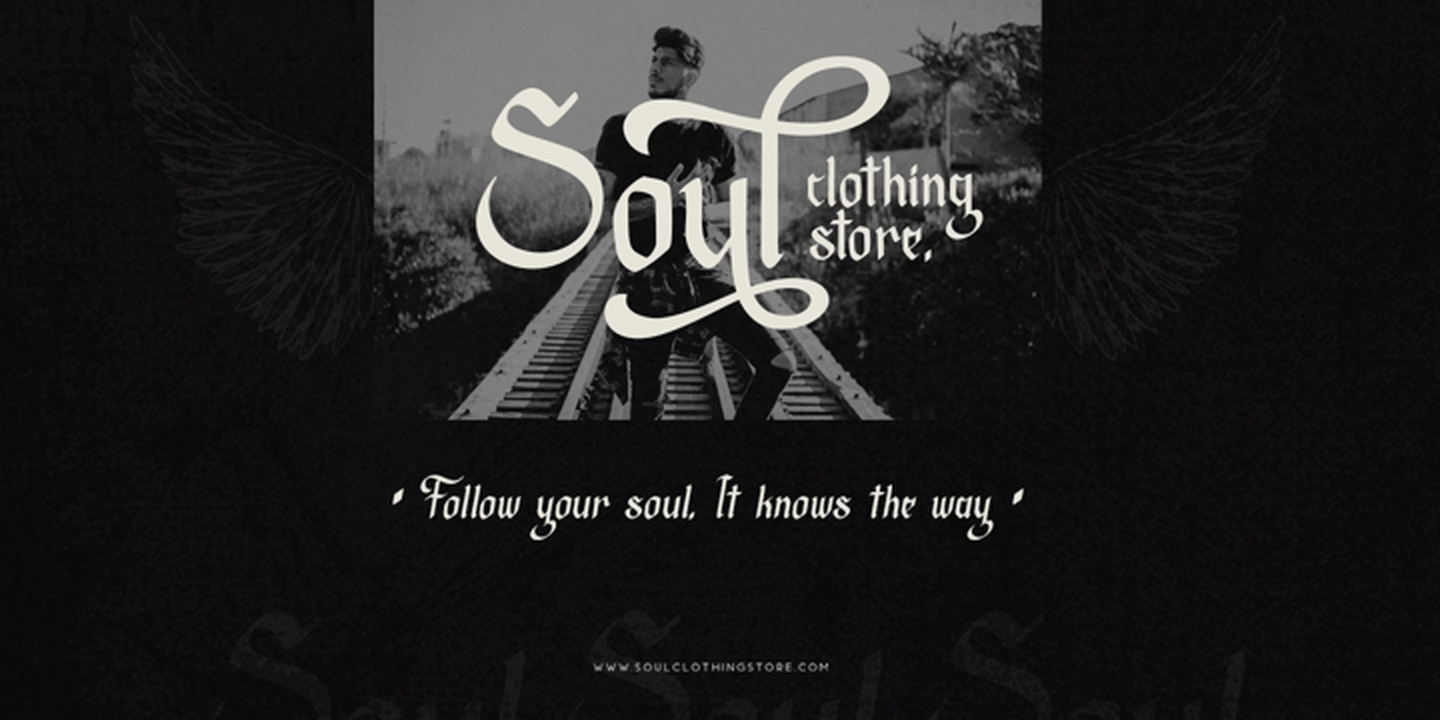
Empirelines Font Family
Les Empirelines sont la famille des styles de lettres noires, les majuscules et les minuscules étant bien équilibrées. Fournissez une police alternative dans un style de variante minuscule pour rendre la lettre de conception incroyable. Honnêtement, cela fonctionne parfaitement pour les titres, les logos, les affiches, les emballages, les T-shirts et bien plus encore. Utilisation recommandée dans Adobe Illustrator ou Adobe Photoshop avec la fonctionnalité opentype.